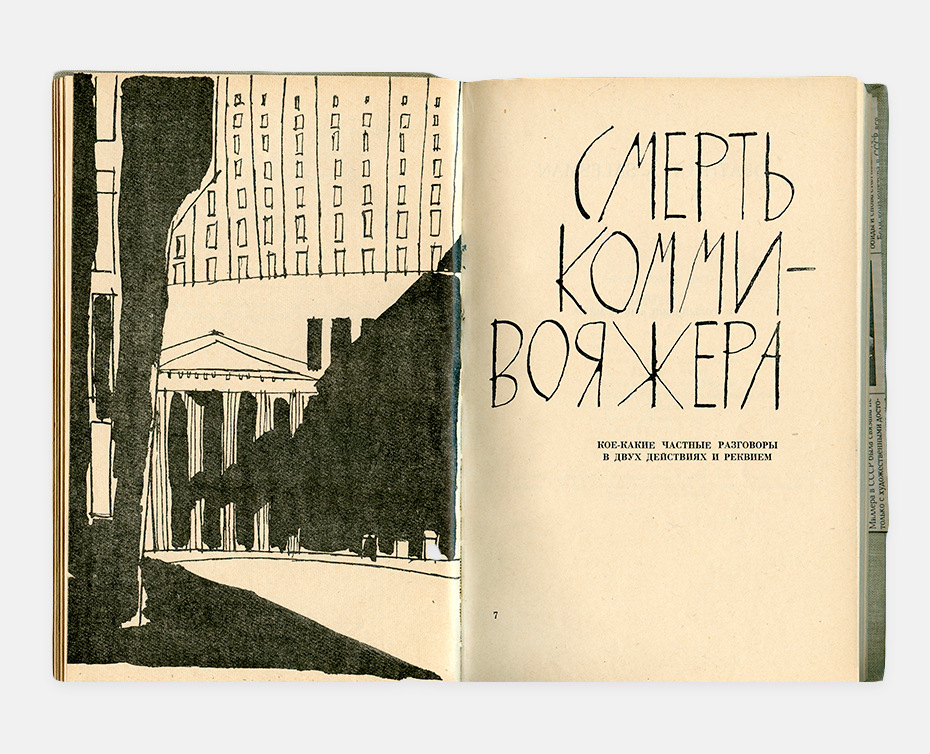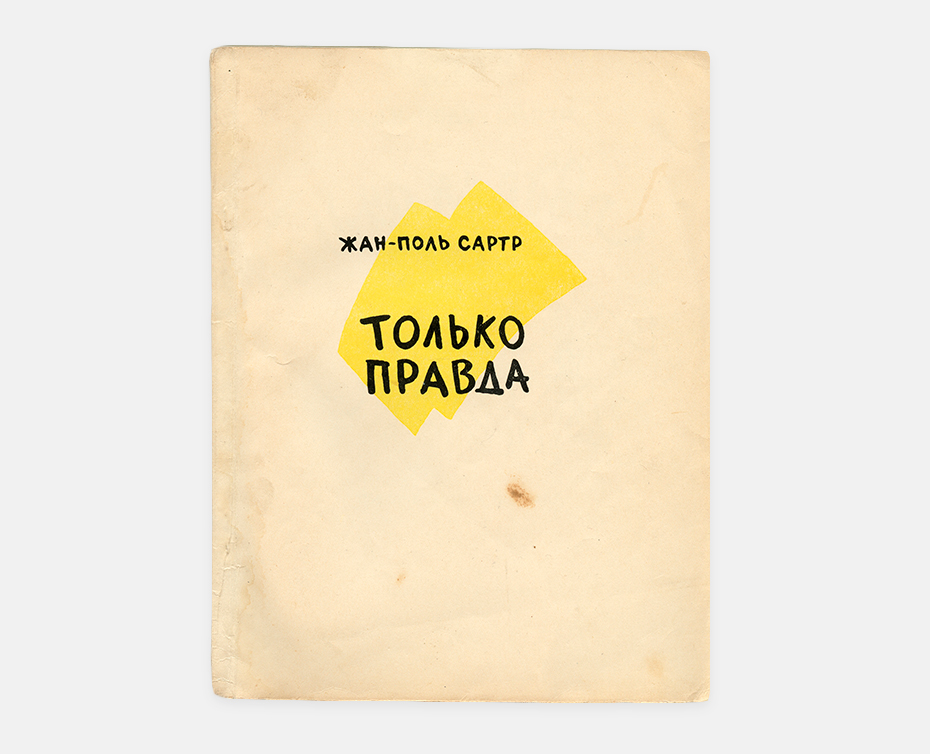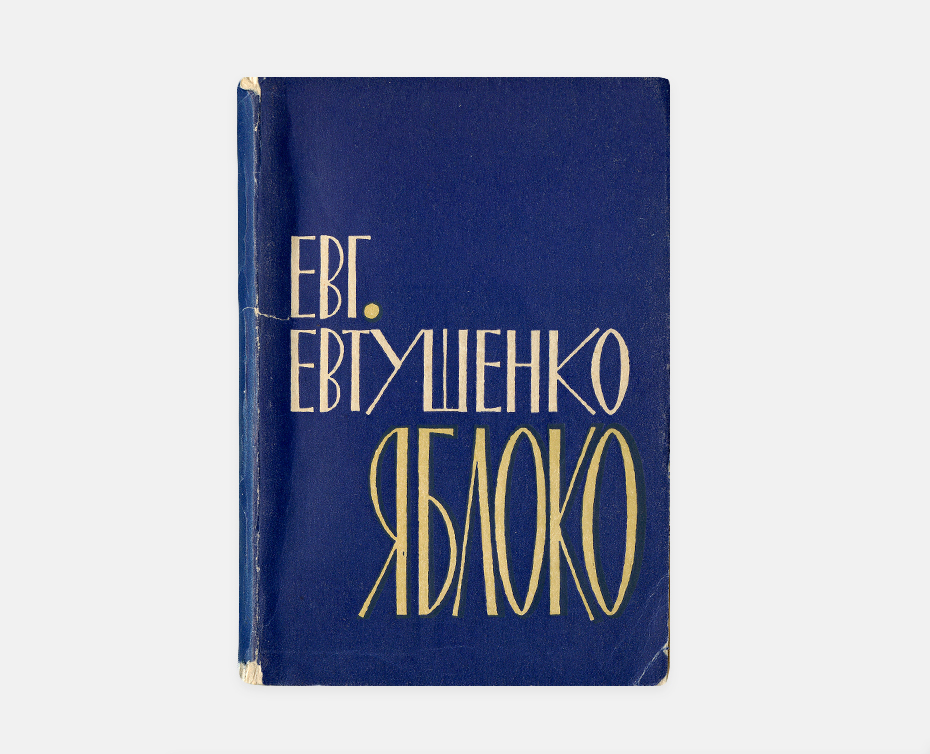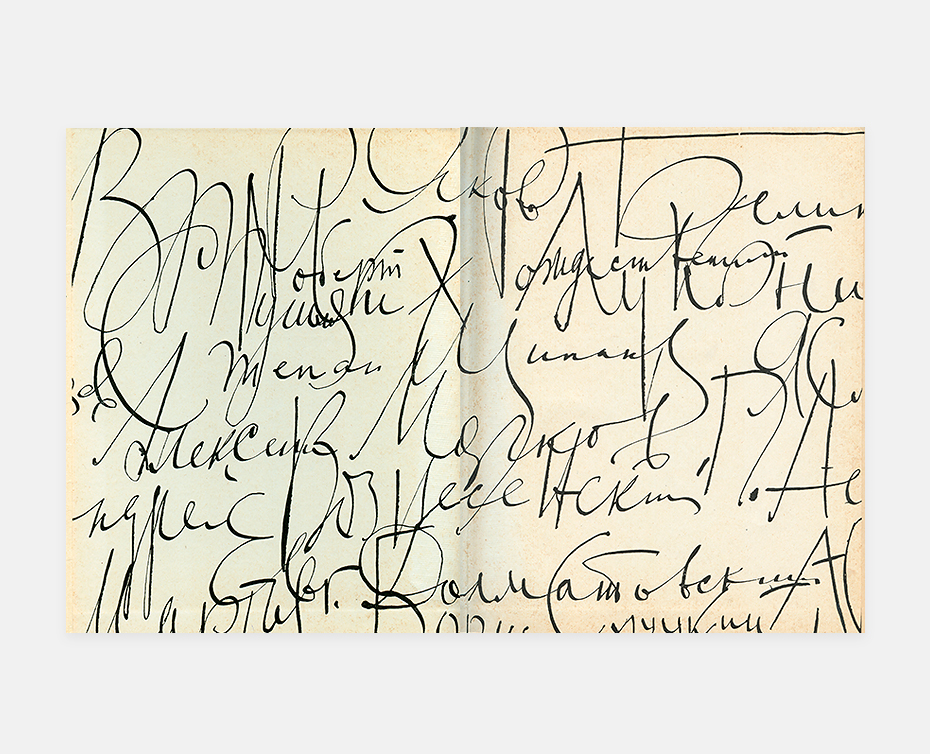
Рисованный шрифт Льва Збарского
Ри­со­ван­ный шрифт Льва Збар­ско­го
Вре­мя Збар­ско­го — вре­мя книг но­во­го сти­ля. Ко­рот­кая от­те­пель (1954–1964) в со­вет­ской жиз­ни и куль­ту­ре кос­ну­лась и про­стран­ства кни­ги, пре­об­ра­зо­ва­ла её со­став­ные эле­мен­ты: пе­ре­плёт­ные ма­те­ри­а­лы, фак­ту­ру, ко­ло­рит, ком­по­зи­цию об­ло­жек и ти­туль­ных ли­стов, ха­рак­тер лет­те­рин­га и сти­ли­сти­ку ил­лю­стра­ций. Гос­под­ство псев­до­клас­си­че­ско­го фа­са­да 40–50-х го­дов в кни­ге с его тор­же­ствен­ны­ми, стро­го сим­мет­рич­ны­ми и од­но­об­раз­но без­жиз­нен­ны­ми шриф­то­вы­ми ком­по­зи­ци­я­ми сме­ни­лось сво­бод­ным, лёг­ким и че­ло­веч­ным ри­со­ван­ным шриф­том. Во мно­гом это бы­ло вли­я­ние за­пад­ной жур­наль­ной и ре­клам­ной сти­ли­сти­ки. Ха­рак­тер­ные над­пи­си «ле­тя­щим» по­чер­ком по­яв­ля­лись по­всю­ду: в пла­ка­тах, ки­но­тит­рах, на упа­ков­ках то­ва­ров и вы­вес­ках. При­от­крыв­ший­ся не­на­дол­го же­лез­ный за­на­вес во вре­ме­на Хрущёва вер­нул мо­ду на гра­фи­ку Пи­кас­со и Ма­тис­са, ко­то­рые ока­за­ли огром­ное вли­я­ние на стиль Льва Збар­ско­го (в этом мож­но убе­дить­ся, рас­смот­рев ни­же ил­лю­стра­ции ху­дож­ни­ка к Ови­дию).
Грим и бу­та­фо­рия в кон­струк­ции кни­ги со­шли на нет — всё ча­ще пе­ре­плёт за­ме­нял­ся мяг­кой об­лож­кой из плот­ной бу­ма­ги, на ко­то­рую на­де­ва­лась вы­ра­зи­тель­ная су­пер­об­лож­ка. «Прав­да ма­те­ри­а­ла», «ком­по­зи­тор кни­ги», «кни­га — еди­ный ху­до­же­ствен­ный ор­га­низм» — лю­би­мые вы­ра­же­ния кри­ти­ков то­го вре­ме­ни. Ху­дож­ни­ки тех лет (и Збар­ский в пер­вую оче­редь) взя­ли в свои ру­ки не толь­ко оформ­ле­ние от­дель­ных эле­мен­тов кни­ги, но и раз­ра­бот­ку ма­ке­та в це­лом: от вы­бо­ра раз­ме­ров по­лей до рас­по­ло­же­ния ил­лю­стра­ций. Всё это бы­ло по­пыт­кой про­тя­нуть ру­ку ти­по­гра­фам-кон­струк­ти­ви­стам 20-х го­дов, со­вер­шив­шим ре­во­лю­цию в со­вет­ской кни­ге. Ре­во­лю­цию, ко­то­рую уже к се­ре­ди­не 1930-х на­силь­но све­ли на нет под ви­дом борь­бы с «фор­ма­лиз­мом».
Од­на­ко пе­ре­осмыс­лить функ­ци­о­на­лизм 20-х в пол­ной ме­ре не уда­лось ни мо­ло­до­му по­ко­ле­нию (ма­ят­ник идео­ло­гии вновь кре­нил­ся впра­во), ни не­мно­го­чис­лен­ным вы­жив­шим ти­по­гра­фам-ре­во­лю­ци­о­не­рам ста­рой гвар­дии: кто-то не смог опра­вить­ся от пе­ре­ков­ки, а кто-то (как, на­при­мер, Со­ло­мон Те­лин­га­тер) при­нял­ся с увле­че­ни­ем раз­ра­ба­ты­вать иную, ри­со­ван­ную, а не ти­по­граф­скую осно­ву в кни­ге. И тем не ме­нее ху­дож­ни­ки-ше­сти­де­сят­ни­ки — Лев Збар­ский, Бо­рис Мар­ке­вич, Юрий Крас­ный, Дмит­рий Би­сти, Юрий Со­бо­лев, Юло Со­остер и мно­гие дру­гие — каж­дый по-сво­е­му вне­сли в ис­кус­ство кни­ги не­по­вто­ри­мый вклад. Книж­ный лет­те­ринг 60-х — не­ис­чер­па­е­мый учеб­ник сво­бо­ды, ко­то­рый мы толь­ко на­чи­на­ем от­кры­вать и ис­сле­до­вать. — Ру­стам Габ­ба­сов
ак-то из­вест­ный ху­дож­ник и учи­тель Льва Збар­ско­го в Мо­сков­ском по­ли­гра­фи­че­ском ин­сти­ту­те Иван Чек­ма­зов по­шу­тил об уче­ни­ке: «Он уже со­всем... Так ри­су­ет, ка­жет­ся, что об­лож­ки де­ла­ет в лег­ко­вой ма­ши­не, ко­гда едет сда­вать ра­бо­ту в из­да­тель­ство!» Это к то­му, что Лев Збар­ский всё де­лал бы­стро, и — вир­ту­оз­но. Это ка­са­ет­ся и шриф­та.
Се­го­дня ди­зай­нер име­ет прак­ти­че­ски без­гра­нич­ные воз­мож­но­сти в вы­бо­ре на­бор­ных шриф­тов для оформ­ле­ния кни­ги, в том чис­ле и в кал­ли­гра­фи­че­ском или ру­ко­пис­ном сти­ле. А как бы­ло 50 лет на­зад? Про­цесс ра­нее был бо­лее тру­до­ем­ким, ко­гда де­ло ка­са­лось лет­те­рин­га. Но если по­смот­реть на об­лож­ки, пе­ре­плёты, су­пер­об­лож­ки и ти­ту­лы книг, оформ­лен­ных Збар­ским, то ка­жет­ся, что осо­бых тру­дно­стей ху­дож­ник то­гда не ис­пы­ты­вал.
Не­сколь­ко слов о ху­дож­ни­ке. Фе­ликс-Лев Збар­ский ро­дил­ся 12 но­я­бря 1931 го­да в Моск­ве в се­мье из­вест­но­го уче­но­го-био­хи­ми­ка Бо­ри­са Ильи­ча Збар­ско­го, про­сла­вив­ше­го­ся уча­сти­ем в баль­за­ми­ро­ва­нии те­ла Ле­ни­на. Ред­кое двой­ное имя отец дал маль­чи­ку в честь двух ува­жа­е­мых им лю­дей: Фе­лик­са Эд­мун­до­ви­ча Дзер­жин­ско­го и учё­но­го-хи­ми­ка Льва Яко­вле­ви­ча Кар­по­ва. Став ху­дож­ни­ком, свои ра­бо­ты он под­пи­сы­вал то Львом, то Фе­лик­сом, но ни­ко­гда по пас­пор­ту — Фе­лик­сом-Львом. Зва­ли же его все Лёвой. Пер­вые опы­ты ри­со­ва­ния он по­лу­чил в Тю­ме­ни, ку­да в 1941 г. эва­ку­и­ро­ва­ли те­ло Ле­ни­на, а с ним на­пра­ви­ли Б. Збар­ско­го и его се­мью. В Моск­ву все вер­ну­лись в 1945 го­ду.
Фе­ликс-Лев Збар­ский. Да­та съём­ки не­из­вест­на.
В 1949-м юно­ша окон­чил с се­ре­бря­ной ме­да­лью сред­нюю шко­лу и год про­учил­ся во ВГИ­Ке. В 1950 го­ду он по­сту­пил в Мо­сков­ский по­ли­гра­фи­че­ский ин­сти­тут на ху­до­же­ствен­но-офор­ми­тель­ское от­де­ле­ние ре­дак­ци­он­но-из­да­тель­ско­го фа­куль­те­та. Учё­ба за­вер­ши­лась в 1955-м за­щи­той ди­плом­но­го про­ек­та: оформ­ле­ние кни­ги Вик­то­ра Гю­го «Рюи Блаз» и вы­пол­не­ние бу­кле­та к спек­та­клю с тем же на­зва­ни­ем. У вы­пуск­ни­ка бы­ли от­лич­ные оцен­ки по всем дис­ци­пли­нам, но ди­плом­ную ра­бо­ту оце­ни­ли на «хо­ро­шо». Ви­ди­мо, крас­ный ди­плом вы­пуск­ни­ку По­ли­гра­фа не до­стал­ся ещё и по­то­му, что в ха­рак­те­ри­сти­ке бы­ло ска­за­но: «При­ни­мал уча­стие в об­ще­ствен­ной жиз­ни ин­сти­ту­та, но ком­со­моль­ские и об­ще­ствен­ные по­ру­че­ния вы­пол­нял не все­гда охот­но и до­бро­со­вест­но. Не­до­ста­точ­но дис­ци­пли­ни­ро­ван».
В том же 1955 го­ду со­сто­ял­ся де­бют ху­дож­ни­ка в ил­лю­стри­ро­ва­нии. Он вы­пол­нил оформ­ле­ние и цикл ри­сун­ков для дет­ской кни­ги «Связ­ная Цзинь Фын» Ни­ко­лая Шпа­но­ва. Из­вест­ный в те го­ды ав­тор шпи­он­ских и фан­та­сти­че­ских про­из­ве­де­ний на­пи­сал по­весть для де­тей о во­ен­ном про­ти­во­сто­я­нии На­род­но-осво­бо­ди­тель­ной ар­мии Ки­тая и Го­миньда­на. Сю­жет — 12-лет­няя ге­ро­и­ня по­бе­жда­ет ма­тёрых чан­кай­ши­стов. О шриф­те мож­но ска­зать един­ствен­ное: ху­дож­ник так на­чер­тал на­зва­ние кни­ги и нашёл та­кие ед­ва за­мет­ные эле­мен­ты, что уга­ды­ва­ет­ся намёк на ки­тай­ское со­дер­жа­ние без при­выч­ных иеро­гли­фи­че­ских ими­та­ций.
Ни­ко­лай Шпа­нов. Связ­ная Цзинь Фын. М.: Гос. из­дат. дет. лит., 1955. Ти­туль­ный лист.
В 1956 го­ду Збар­ско­му до­ве­ри­ли в Го­сли­тиз­да­те офор­мить том из­бран­ных про­из­ве­де­ний Юрия Оле­ши. Это был про­рыв. Не­мно­го­слов­ное, но очень изыс­кан­ное оформ­ле­ние при­влек­ло к се­бе вни­ма­ние мно­гих. Прав­да, в «Со­вет­ской куль­ту­ре» по­яви­лось пись­мо в ре­дак­цию не­ко­е­го ка­лу­жа­ни­на А. Бе­ля­е­ва под ха­рак­тер­ным на­зва­ни­ем (Бе­ля­ев А. Вме­сто ил­лю­стра­ций — вы­кру­та­сы // Сов. куль­ту­ра. 1957. 11 июня). Та­кое бы­ло вре­мя... Но обра­тим­ся к кни­ге и её ти­туль­но­му ли­сту. Имя ав­то­ра сде­ла­но ри­со­ван­ным гро­те­ском, но о и ю вы­пол­не­ны без при­выч­ных на­плы­вов спра­ва и сле­ва. А ш как-то умест­но име­ет не­оди­на­ко­вые вер­ти­каль­ные ли­нии. Цве­ток вме­сто точ­ки — это то­же не­ожи­дан­но. На­зва­ние кни­ги «Из­бран­ные со­чи­не­ния» вы­пол­не­но ле­тя­щим по­чер­ком, и вся над­пись на­по­ми­на­ет фраг­мент, слов­но вы­ре­зан­ный из ру­ко­пи­си пи­са­те­ля.
В 1956 го­ду ху­дож­ник на­чал со­труд­ни­чать с из­да­тель­ством «Ис­кус­ство» (здесь он сту­ден­том в 1954–1955 го­дах про­хо­дил прак­ти­ку). Рас­смот­рим две кни­ги это­го пе­ри­о­да, на пер­вый взгляд раз­ные (и для раз­ных ре­дак­ций), но оформ­лен­ные как буд­то се­рий­но.
Пер­вая — это «Солн­цем пол­на го­ло­ва» по­пу­ляр­но­го ки­но­ак­тёра и пев­ца Ива Мон­та­на. Вто­рая — пье­са Жан-По­ля Сар­тра «Толь­ко прав­да». У книг оди­на­ко­вый фор­мат — 70×92/16. В обе­их кни­гах — об­лож­ка и су­пер­об­лож­ка. Обе су­пер­об­лож­ки — жёл­тые. На об­лож­ке кни­ги Ива Мон­та­на текст бе­лый на жёл­том фо­не. Та­кое не все­гда лег­ко чи­та­ет­ся, но на фо­не об­щей трёх­цвет­ной ком­по­зи­ции вы­гля­дит не­пло­хо. Ти­тул же ре­шён при­выч­но: спо­кой­ное на­чер­та­ние име­ни ав­то­ра, хо­тя и не­при­выч­ное по ри­сун­ку, и раз­ма­ши­стое — на­зва­ния кни­ги, по-на­сто­я­ще­му «сол­неч­ное». При­ме­ча­тель­на об­лож­ка, скры­тая под су­пер­об­лож­кой. Мож­но ли счи­тать нот­ную за­пись шриф­то­вой ра­бо­той? Впро­чем, Збар­ский на нот­ном ста­не раз­ме­стил весёлень­кие цве­точ­ки.
Сво­бо­дин А. За­пад­ная дра­ма­тур­гия в ил­лю­стра­ци­ях Ф. Збар­ско­го // Те­атр. 1956. № 6. С. 175.